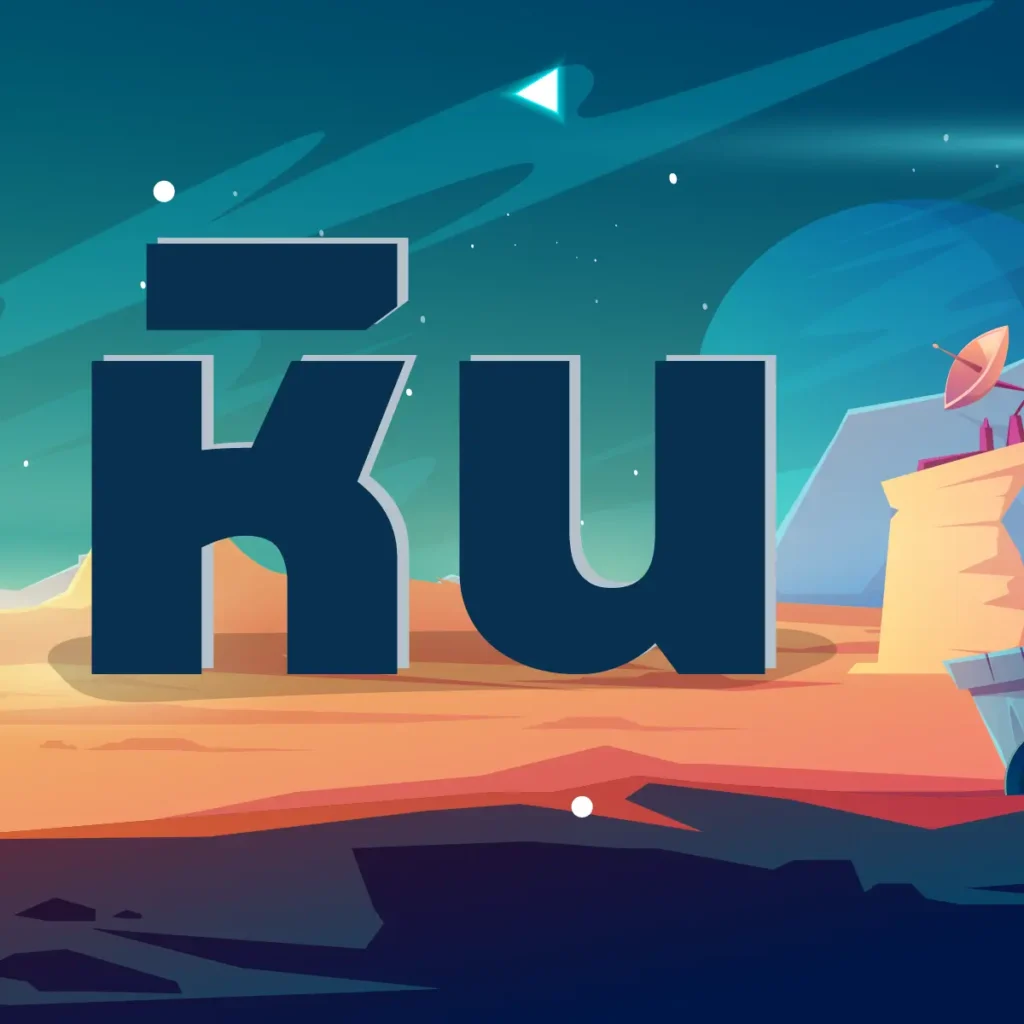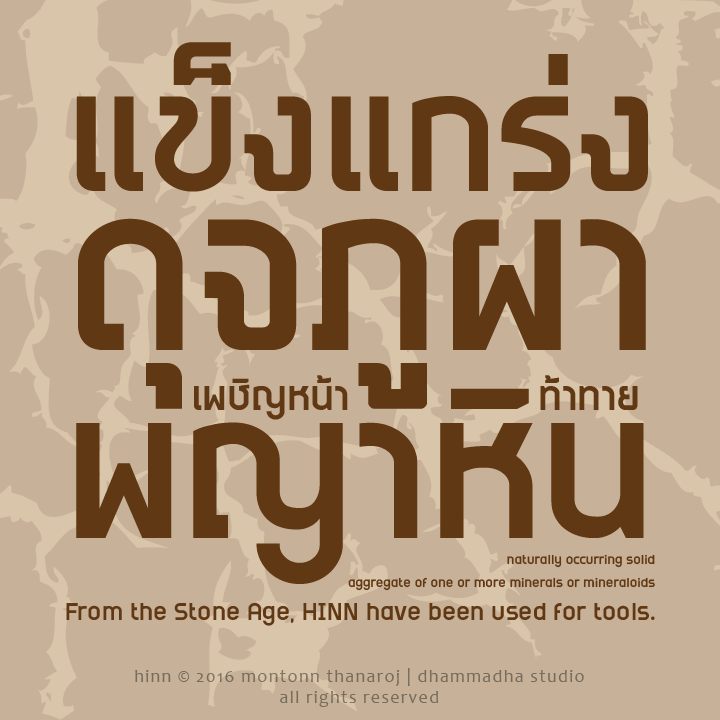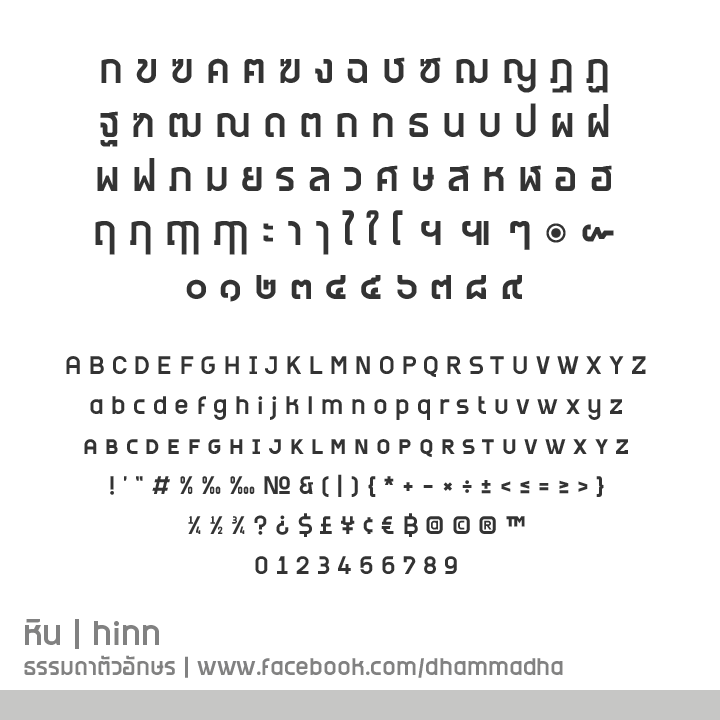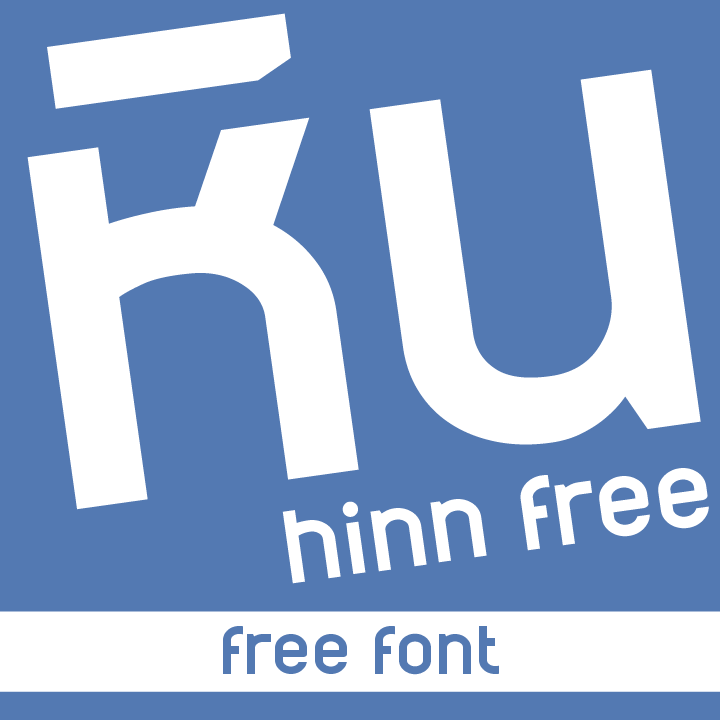
ฟอนต์ชุดนี้ เป็นฟอนต์ชุดแรกที่เริ่มทำขึ้นพร้อมๆ กับฟอนต์ “ป้ายไม้” มีการปรับรูปแบบหลายครั้ง จนเริ่มเข้าที่เข้าทาง เลยมีการเปลี่ยนชื่อเดิม เป็น “หิน” ที่มีทั้งเหลี่ยม ทั้งมน